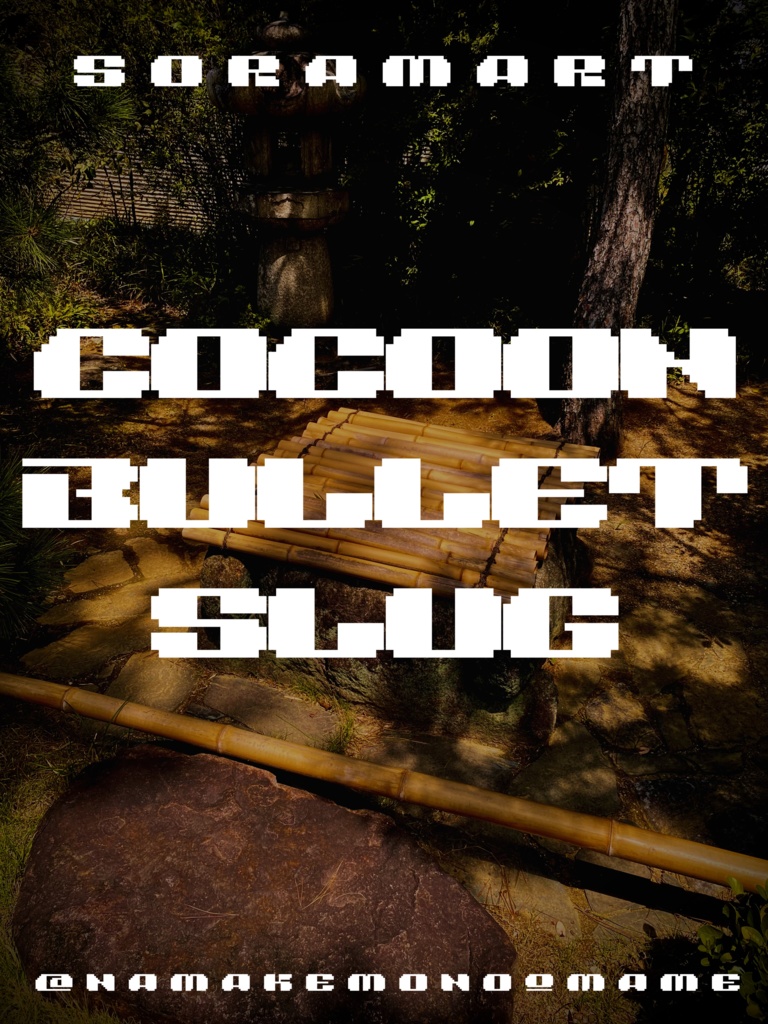
そらマートフォントデータ”Cocoon Bullet Slug”Digital2,500 JPYAdd to CartBuy a GiftAbout Gift離れてみると ”丸み” を感じるドット調極太フォント "Cocoon Bullet Slug" です。 「TrueTypeフォントファイル」という形式です。 ダウンロードした後、Zipファイル内のデータをインストールしてお使いください。 このフォントは商用利用可となっております。 お客様の制作・創作活動のお役に立てれば幸いです。 ※使用上の注意事項などは、添付のReadmeをお読みください。そらマートVisit FANBOX!Fontsフォントデータ”Crushed Can Serif Empty”そらマート2,500 JPYFontsフォントデータ”Crushed Can Serif Wide”そらマート0 JPYFontsフォントデータ”Crushed Can Serif”そらマート0 JPYFontsフォントデータ”Dolce Cube Tall”そらマート2,500 JPYFontsフォントデータ”Dolce Cube”そらマート2,500 JPYFontsフォントデータ”Eight-bit Quest Wide”そらマート2,500 JPYFontsフォントデータ”Eight-bit Quest”そらマート2,500 JPYFontsフォントデータ”Tonik Crate”そらマート2,500 JPYFontsフォントデータ”Vapor Sprout Edge”そらマート2,500 JPYFontsフォントデータ”Vapor Sprout Wide”そらマート2,500 JPYFontsフォントデータ”Vapor Sprout”そらマート2,500 JPYFontsフォントデータ”Star Shoot Ray”そらマート2,500 JPYFontsフォントデータ”Star Shoot Black Wide”そらマート2,500 JPYFontsフォントデータ”Star Shoot Black”そらマート2,500 JPYFontsフォントデータ”Mars Invader Balloon”そらマート2,500 JPYFontsフォントデータ”Mars Invader Wide”そらマート2,500 JPYFontsフォントデータ”Mars Invader”そらマート2,500 JPYFontsフォントデータ”Rock Cut Serif”そらマート2,500 JPYFontsフォントデータ”Rock Cut Drop Wide”そらマート2,500 JPYFontsフォントデータ”Rock Cut Drop”そらマート2,500 JPYSee More